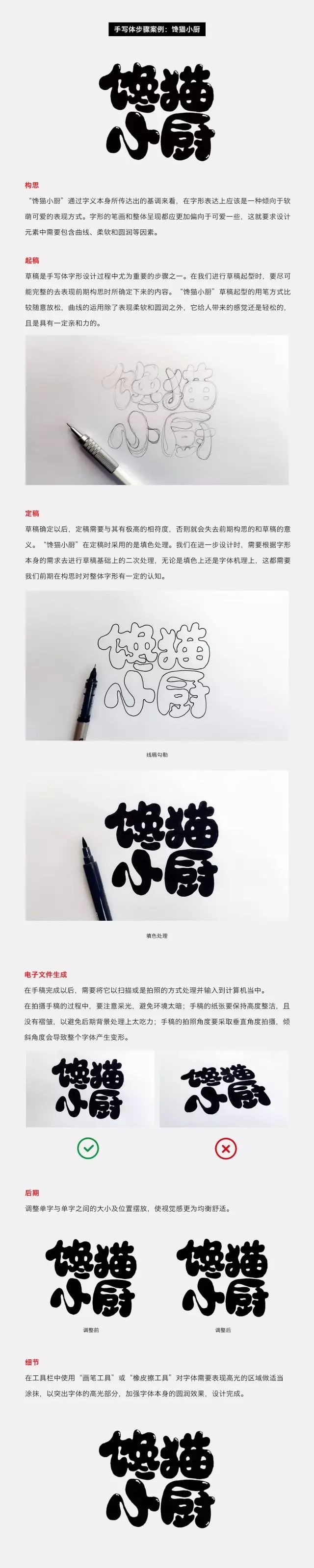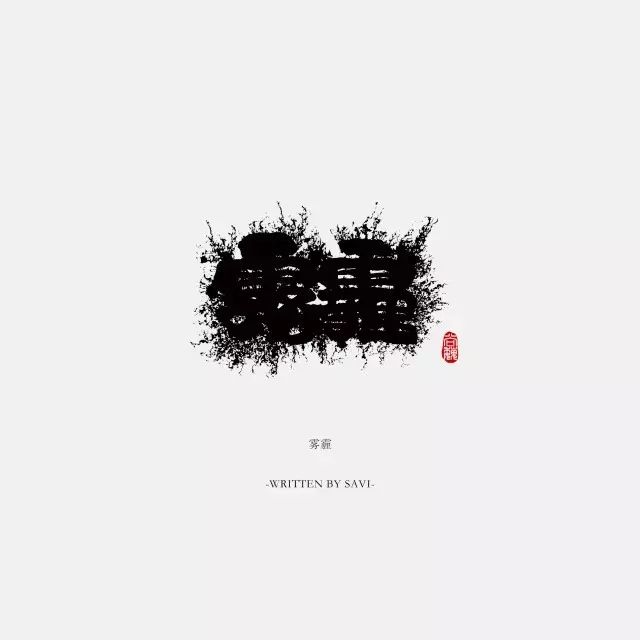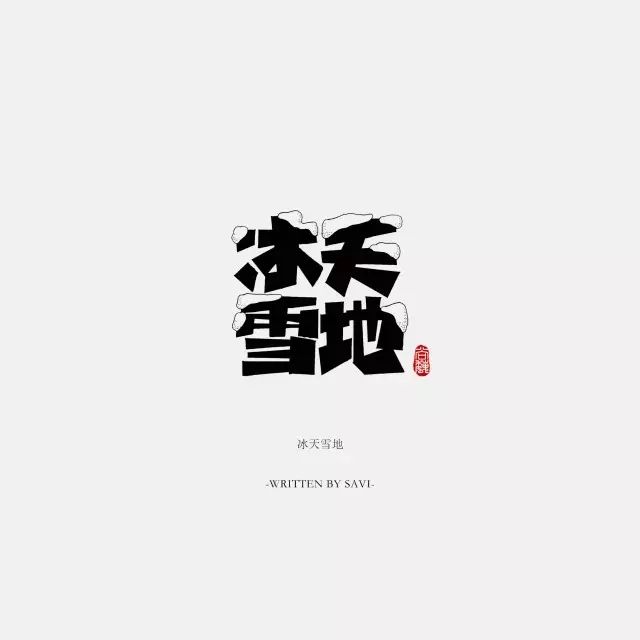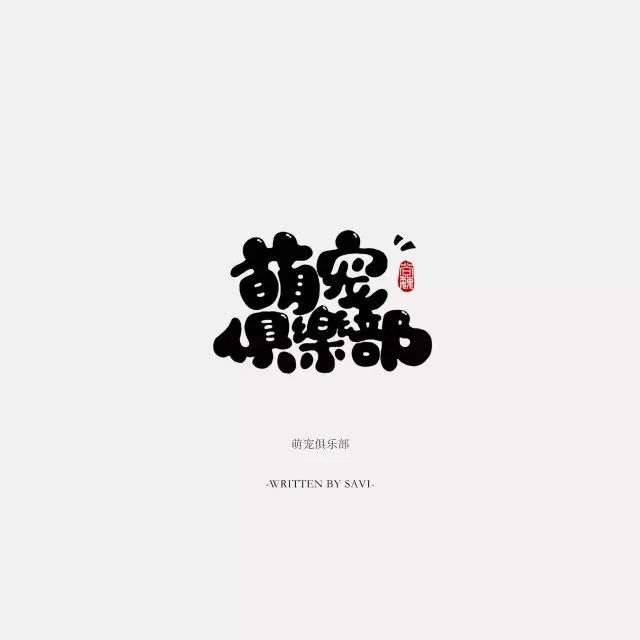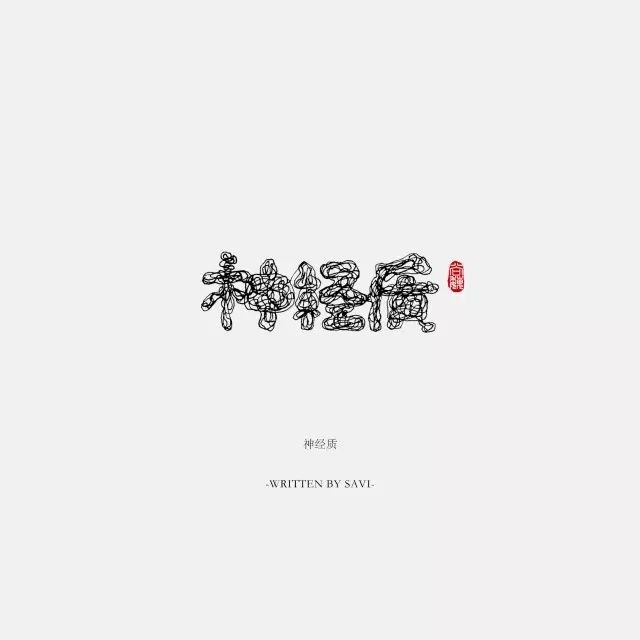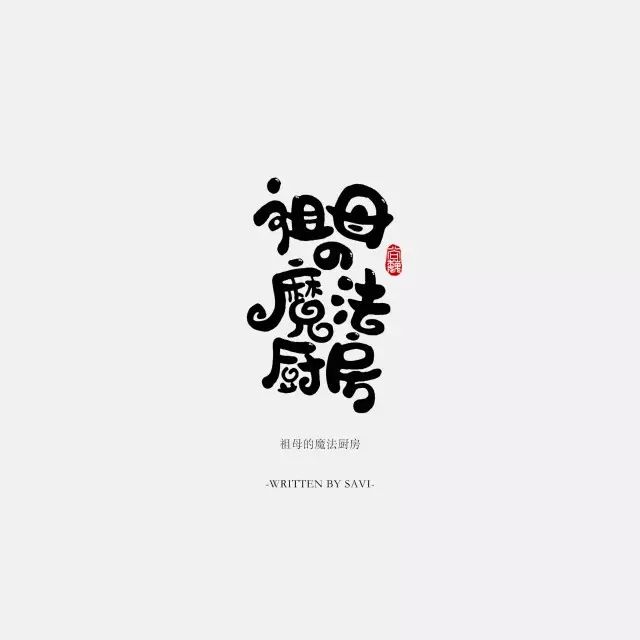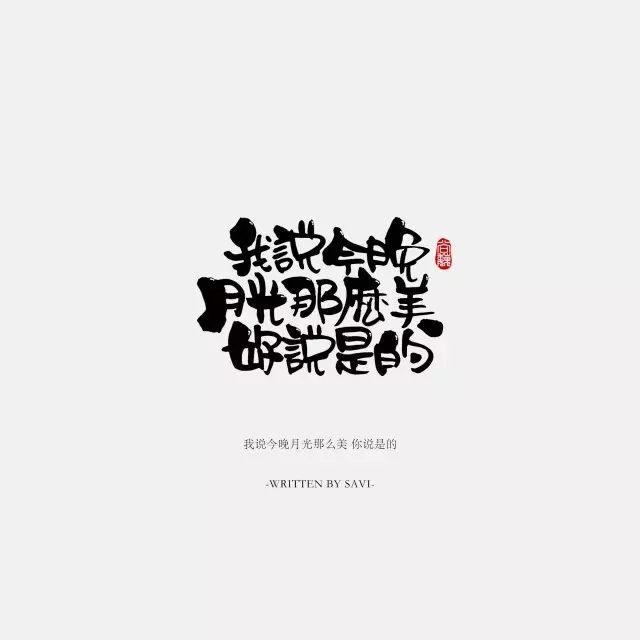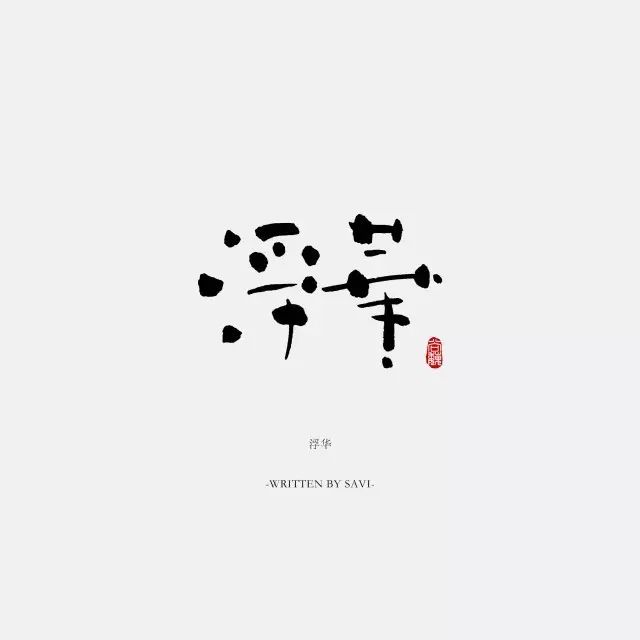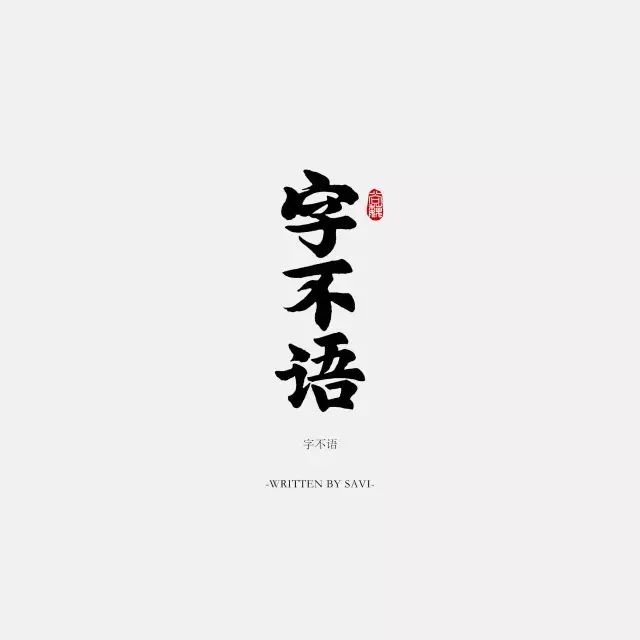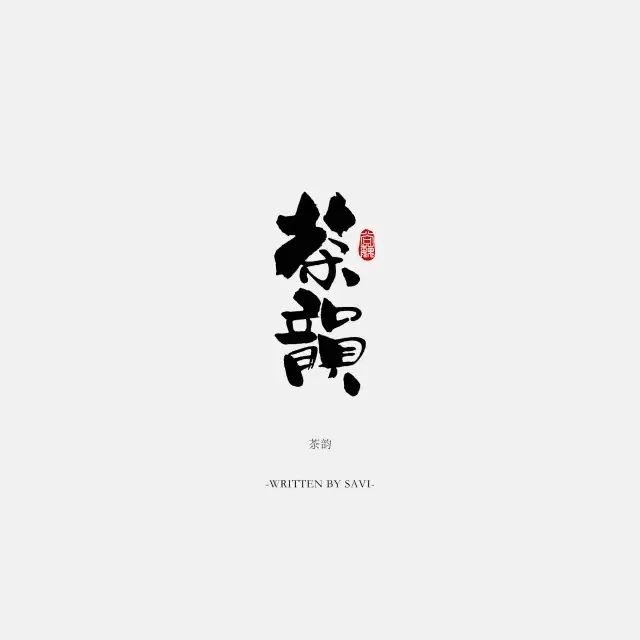
如何才能写一手好字?一些重要的思路总结
我是尚巍,我是一个写字的。
如今在很多场合下,会常常遇到一些朋友问我如何才能写一手好字。其实面对诸多这样的类似问题,答案只有一个:练习。因为练习是唯一的提升方式,写字没有捷径。
当你掌握了一定的字形基础之后,便可以开始去做一些手写体的设计。自我提出“手写体字形”这个概念之后,我也一直在探索,设计方法有很多,我简单做个思路上的总结,希望能带给初学者一点点启迪和帮助。 但最关键的,是你要拿起笔,并且学会坚持。
如下,一些练习:
最后,没什么说的。
只有一点:坚持,坚持就好。